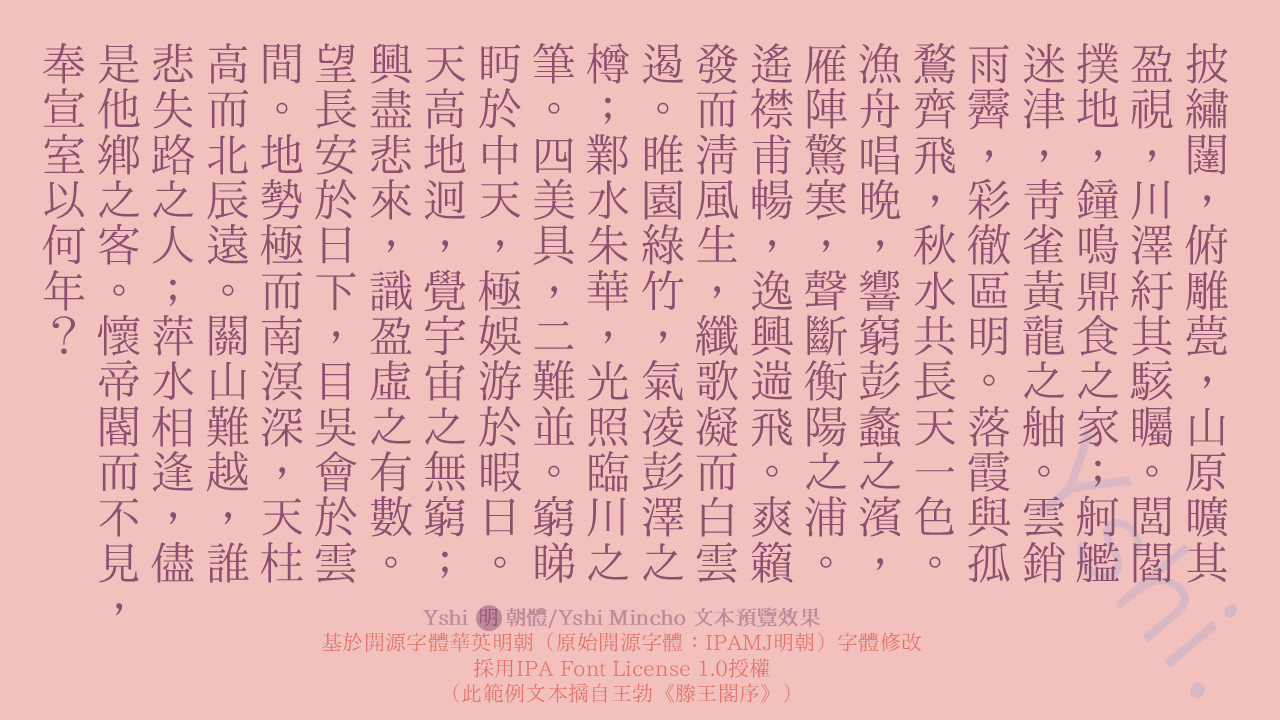
Y式明朝是一款别具一格的中文字体,它并非完全原创,而是精心整合并发展了以往多款字体的精华。这款字体明确指出其衍生自并综合了“华英明朝”与“IPAmj明朝”的骨架及笔画特质,同时在设计过程中也吸纳了“霞鹜新致宋”与“霞鹜致宋”的一些元素,特别是在追求字体结构的平衡和视觉的舒适度方面。具体来说,它主要以“华英明朝”和“IPAmj明朝”这两款经典日系明朝体为基础,进行了深入的调整和适配,以满足中文排版的需求,并且有选择地融入了“一点明朝”的若干设计特征。
该字体的核心设计理念是坚守传统字形。它致力于恢复和运用旧字形的笔画形态与结构方式,这使其字形风格显得古朴而正统,与一些采用新字形(即印刷体习惯写法)的现代字体有所区别。例如,在处理“走之底”、“心字底”等部件时,它可能更倾向于遵循传统书写或古籍印刷中的样貌。作为一款中文字体,其修改与优化工作的重点在于确保简体中文、繁体中文乃至日文汉字的字形都能得到恰当呈现。同时,Y式明朝秉承了其源字体的精神,是一款开源字体,这意味着用户可以免费使用、研究和再创作,为中文排版设计社区增添了又一富有传统韵味的选择。